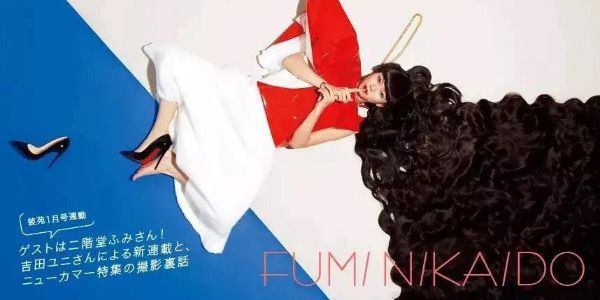
一说到日本设计,相信很多人的脑海中都会想到“极简主义”,的确,日本设计总是会给人一种清新简洁、极简易用的印象,融合传统的日系文化,造就出一种独特的风格,并且传播到世界各地,产生深远的影响。
但是如果你认为日本设计只是极简?那就大错特错了,日本设计才不止极简呢,例如今天要给大家介绍的这位近年来日本设计界炙手可热的新锐设计师——吉田ユニ/ Yuni Yoshida。
吉田ユニ的创作涉及广告、 唱片封面、影像、装帧等多元设计领域,她颠覆想象的作品总是给人带来一种鲜明的色彩对比和神秘的艺术氛围,尤其在海报设计方面,吉田ユニ利用大胆独特的色彩和超现实的表现形式,呈现出不一样的日本设计风格,而这种超现实的风格便成为了吉田ユニ的标签。
吉田ユニ是眼下日本设计界炙手可热的平面设计师和艺术指导,她以鲜活的色彩和具有强烈视觉冲击的作品而闻名,是日本最受瞩目的年轻女性设计师之一。就算你不知道她的名字,也一定看过她的作品:Perfume 的「Cosmic Explorer」专辑视觉设计;星野源单曲「恋」的封面; 日本话题女王渡边直美举办个人展时那组火爆微博的惊艳海报……都出自吉田ユニ之手。
吉田ユニ的主要代表作包括 Laforet 原宿、野田秀树演出的舞台剧 THE BEE 、半神的艺术指导,木村 KAELA、Perfume、星野源的 CD 视觉设计,以及渡边直美的艺术指导等。同时她也在时尚杂志「装苑」上进行专栏连载,还受到 KIRIN、LOWRYS FARM 等国内外企业和品牌的青睐,邀请吉田ユニ为他们制作广告。吉田ユニ于 2016 年获得东京 ADC 奖。
吉田ユニ,1980年出生于东京,从初中开始就读女子美术大学附属中学,学习绘画和素描,高中开始研习油画,进入大学后开始学习设计及广告,并对广告业产生了浓厚的兴趣。
第一次接触平面媒体是在大学三年级的广告课上。后来这个喜欢独自作业的少女也并不固步自封,因为想要尝试全新的事物,所以在就职时选择了与大学专业完全不同的平面设计,像是一脚踏进幻想国的冒险爱丽丝。
吉田ユニ是一位年轻的设计师,所以我们没有必要像研究老一辈设计师那样去深挖她的经历,与其如此还不如单刀直入,直接去了解她的作品。这里我们从吉田ユニ的作品中总结出几个关键词,下面就让我们一窥究竟吧!(后文中的吉田ユニ我们简称吉田)
在吉田的作品里,Perfume、木村 KAELA、渡边直美、Kyary Pamyu Pamyu、水原希子……每一个人在她的作品里都像被放进完全不同的维度里,展现出令人想象不到的一面。但是要说最有代表性的,还属渡边直美。
可能有的人不是很了解渡边直美,她的 Instagram 关注者位居日本首位,是日本当红的新生代搞笑女王。而吉田和超级可爱的直美是好友,也常一起合作,不论是直美的个人服装品牌「PUNYUS」或是演唱会,都能看到吉田替直美量身打造的设计作品。
每次在做艺人宣传企划之前,吉田都会先与他们交流并观察他们的个人特点,然后再思考如何最大化发挥他们的特质,最后将这些特质融入设计之中。
直美告诉吉田自己最喜欢的两样东西是“食物”和“时尚”,于是我们就看到了一个充满吉田风格的渡边直美。她将直美“重量级”的身材作为设计焦点,在表现出直美的谐星个性之外,华丽的装饰风格配上直美认真的表情,使整体呈出一种戏剧感,同时又不失幽默滑稽的表现力。
在先前时尚杂志「装苑」1月刊的拍摄中,渡边直美就戴上了澎澎头,穿上了皮草洋装,呈现出极致的时尚感。
除此之外,吉田也利用擅长的超写实技巧,将渡边的双脚化身为鲜艳的口红、成为可口的小笼包、化身大型冰淇淋等等。
▴ PUNYUS 2017 春夏系列
吉田和直美的合作还不止于此,在这之后,吉田设计的 PUNYUS 2017 春夏系列,整体的立意点定位在夏天最受欢迎的 BBQ 上,将作为代言人的渡边直美设计成了 BBQ 烤串的形象,同时也展现了最新一季的服装,直接让夏季变得可视化,令人印象深刻。
这两张海报的设计也充满着吉田风格,在视觉上创造出高对比与超现实的视觉表现,也延续了渡边直美个展主视觉的调性。
▴ 渡边直美全球演唱会巡演的主视觉
吉田十分执着于使用道具,通过实物拍摄来完成作品,虽然她的作品中充满了不符合现实尺寸、漂浮在空中、变形的东西,看起来像是 CG 特效,但却都是实物。或许正是因为坚持使用实物,使得吉田的作品虽然天马行空,却看上去十分自然,毫无违和感。
吉田担任了星野源多张单曲、专辑的封面设计。星野源是日剧「逃避虽可耻但有用」的男主,这部剧的主题曲「恋」也由他演唱。随着这部剧的爆红,很多人对「恋」这首歌也不会陌生。
▴ 星野源热卖单曲「恋」的封面
「恋」封面运用了鲜艳的黄色,星野源的白衬衫上画着女性手臂,仿佛被妹子拉扯一般,这张封面在当时引起了很大的关注。
▴ 星野源的专辑「Yellow Dancer」封面
星野源 2015 年发售的的第四张专辑「Yellow Dancer」封面同样由吉田设计,吉田利用各种物品建构出来的装置艺术,就像是穿和服插著髮髻的日本传统妇人,一眼看上去花魁的剪影,仔细观察就会发现只是书籍盘子等家居杂货重迭在一起。这一富有创意的设计在当时获得很大的反响,吉田也凭借此作品获得了2016年日本唱片封面设计大奖。
▴ 「POP VIRUS」专辑封面
▴ 「Family Song」专辑封面
▴ 「DORAEMON」专辑封面
▴ 吉田为星野源 MV 集设计的主视觉
「装苑」是一本日本月刊女性时尚杂志,该杂志成立于 1936 年,是日本第一本时尚杂志,也是仍在出版中的最古老的日本时尚杂志。
从 2016 年起,吉田每月都会在「装苑」的「PLAY A SENSATION」板块连载。连载中她与许多人气艺人合作,以其独特的世界观给读者带来了诸多惊喜。除了连载之外,吉田也担任过「装苑」的封面和一些特别企画板块的视觉设计。
「装苑」是一本“モード系”的时尚杂志,中文翻译过来是“摩登”的意思。“摩登”这一词汇在国内已不常用,或许我们可以将其解释为“超前的潮流感”,这正与吉田的世界观相契合。
▴ 吉田为「装苑」75 周年的纪念所做的视觉设计
为纪念「装苑」75 周年而制作的这一作品,共计使用了1300期「装苑」。吉田分别为每册图书制作书皮,最终用书背将放置于书架上的1300期「装苑」拼合成模特的肖像,然后进行印刷和拼接。吉田凭借这一巨型作品获得了 2016 年东京 ADC 奖。
吉田的作品中常利用肢体表现,利用错位或是加入迥然不同的元素,经过精密计算和反复试验,创造出令人为之震撼的视觉效果。她对于实物有着异乎寻常的执着,也对实物有着独特的运用方式和视角。
为个人展专门制作的作品,用女孩的身体来表现 26 个字母,尽管是平面的创作却像是一场舞台剧,有动态、肢体语言和丰富的视觉,甚至还有标点符号,很有日系的可爱风。
“用人体表现字母其实我不是第一个这么做的人,开始是觉得这样很可爱,于是就去做了这组设计,后来再完成的过程中,我发现肢体动作的表现比我想象中还要具有戏剧感,每一个字母或符号,单独去看它,它都可以成为一种独立的表现。也是完成这一组设计之后,它让我在之后的人体造型上有了更多的想法。”
▴ Perfume 专辑「Cosmic Explorer」
吉田因为鲜艳独特的作风备受时尚业界的青睐,她多次为日本的时尚百货 LAFORET 进行视觉设计,除此之外也为其他日本海内外的百货公司制作广告。
▴ 川上未映子书籍封面设计
为日本小说家、歌手川上未映子设计的书籍书封,将人体上下部位错置后造成的奇幻效果,令人不得不多看两眼。
以女性的肢体造型摆出一个衣架,挂上各式各样的配件饰品。很难想像看似温柔婉约的吉田会有如此疯狂的构想,但却在画面呈现上却依旧能维持舒适和谐。
吉田为「WWD」杂志所做的创意企划,让人气模特中条彩未用衣着来表现 26 个字母
▴ 购物中心 Laforet 2012 年圣诞活动海报
吉田非常善于运用人体的肢体动作来创造具有创意的作品,各种搞怪的姿势和场景,带给我们既具有现实元素同时又大开脑洞的视觉画面。
在吉田的设计中,甚至连头发也可以成为几何元素,强烈的形式主义将画面统整、归纳,由此也可以看出日式追求规律与工整的表现风格。
将头发变成几何元素,并利用颜色产生对称或对比,就像是把人像丢到电脑里进行编排对齐,整体使用温和的粉色系,展现女性甜美的一面。
吉田很在乎拍摄的主题及被摄物的结合,2013 年她为东京时尚周设计的奔驰广告,巧妙结合了 3D 技巧,这是第一次运用车子在她的作品里,除此之外,她也将汽车以水平角度呈现,虽然很少有人这样表现车子,但她觉得一台行驶在墙上的车是非常有力量,而且符合时尚女人的形象。
在吉田的创作中,还有一大主题就是表现女性,也许是因为吉田本身身为女性的原因,她总是从自己的视角和对女性理解出发,为我们呈现出不一样的女性之美与超现实的力量。
▴ 小松菜奈为 Zoff 代言的广告海报
在吉田眼中,好的作品应该“一气呵成”,只有这样才会带来意料之外的结果,并让她在创作中可以进行更深入的思考。“我擅长影像合成,但是‘一气呵成’能让团队中的每个成员都更加积极地关注工作中的每个细节,而且我认为这样拍摄出来的作品意义更深刻”。
▴ Hikarie 百货的杂志封面设计
▴ 吉田为 Lumine 百货设计的活动海报
吉田为女演员臼田麻美以“圆眼镜里飞出的泡泡”为概念进行的拍摄,展现出麻美的不同表情。
吉田为模特玉城 tina 以“被装饰在玻璃杯里的帕妃圣代”为主题进行的拍摄,来发掘 tina 最甜美并且最令女孩子们向往的一面。
吉田拍摄的实力女演员安藤樱,角色多变、造型也千姿百态的安藤樱,裸身戴上首饰,“穿”上了一件仅以首饰构成的衬衫,展现出最本质的一面。
之前我们提到过的吉田在「装苑」上连载的专栏「PLAY A SENSATION」,每月请一位演员或者模特,演绎一组充满玩心的照片,总会让人发现这些明星们与平时形象完全不同的美。
担任歌手木村 KAELA 的杂志视觉设计,人体彩绘的错视也是吉田常用的手法之一。
▴ 台湾省百货公司「新光三越」初夏购物节主视觉
台湾省的新光三越也邀请过吉田为百货公司购物季的宣传文宣设计封面,这次合作真的让眼睛为之一亮,通常我们拿到周年庆之类的广告单看完资讯就会丢掉,而这充满设计感的文宣根本意图是让人收藏。
肢体表现已经无法满足吉田的创作欲望了,于是食物在她手里也创造出了惊人的视觉效果。她让水果蔬菜、蛋糕甜品本身丰富的色彩发挥作用,这些“不会说话的”家伙似乎一瞬间也被赋予了极强的“生命感”。
与西武百货的合作,由礼盒、盘子、假发等元素组成星际大战里的角色。
▴ 餐具和食物组成的女子
▴ 华歌尔时尚内衣品牌 Ful Fru
吉田为内衣品牌 Ful Fru 所创作的系列广告,同样简约的元素却富有层次,加上强烈的色彩组合,一次表现“可口”与“美观”的两种感官。将水果融入时尚内衣品牌的设计,新鲜有趣又让人看了口水直流。
在这些维度多变色彩丰富的作品背后,始终有着吉田自身的坚韧品格作为支撑。从小到大都没什么改变的性格和行事方式,让她在面对工作的时候也从未考虑过妥协,也不被他人的观点所左右。一旦着手开始工作,就绝不会放手,一心不乱地朝目标前进。
然而她却绝不冥顽固执到底,反而手腕柔软,只要立场和想法能传达出来,那么最终展示的成果与最开始设想的不一样也没有关系。
吉田善于表现女性特质和超现实的艺术手法从来都不是割裂开来的,而是将二者巧妙的结合,于是我们就看到了大量充满奇幻、不可思议的女性主题作品。
吉田的强烈风格和执着心到底来自哪里?她说,大概来自于她的“从一而终”。2014年举办个展的时候,她的小学同学来看她,跟她说“吉田和小时候一样,一点也没有变啊”,这应该就是最好的解释。最后我们来看一下吉田的展览:
吉田ユニ,一个把平面变成“戏剧舞台”的设计师,她的设计虽然最终落于平面,却又把不同领域的艺术融合在一起,形成了独具特色的艺术风格。她在艺术与商业中找到完美的平衡,用属于她自己的方式展现了日本文化的独特性。